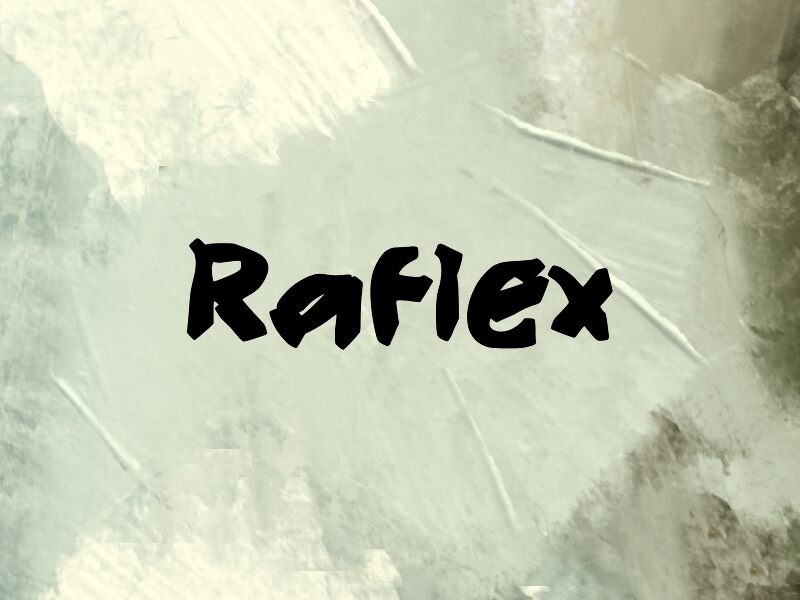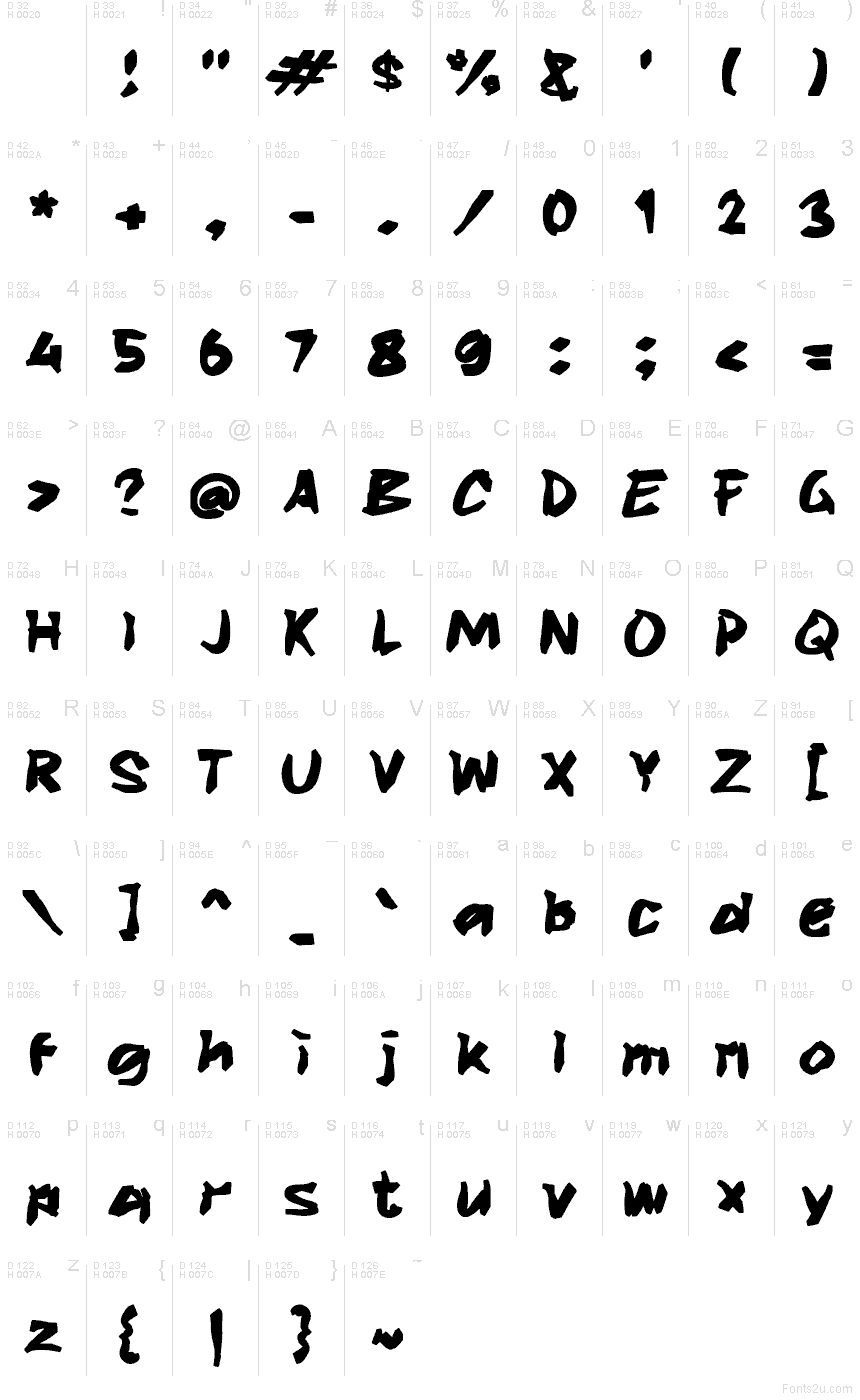
Raflex
Raflex od Wep je bezplatné písmo typu brush, ktoré definujú široké siluety pripomínajúce vystrihovačky z papiera a ostré uhlové zlomy. Vďaka nim pôsobia písmená maliarskym, nie vyhladeným dojmom. Rytmus sady zostáva úderný a nepravidelný, pričom hrubé spoje a vyrezávané vnútorné priestory jej dodávajú energiu surového plagátu.
Raflex je tak prirodzenou voľbou pre hudobné letáky, streetwearovú grafiku, obaly, náhľady videí na YouTube a krátke nadpisy, ktoré vyžadujú surový maliarsky vzhľad. Kompaktné, blokové tvary dodávajú logám a názvom akcií vizuálnu váhu, čo oceníte najmä vtedy, keď hľadáte niečo výraznejšie a viac ručné, než je uhladené skriptové písmo.